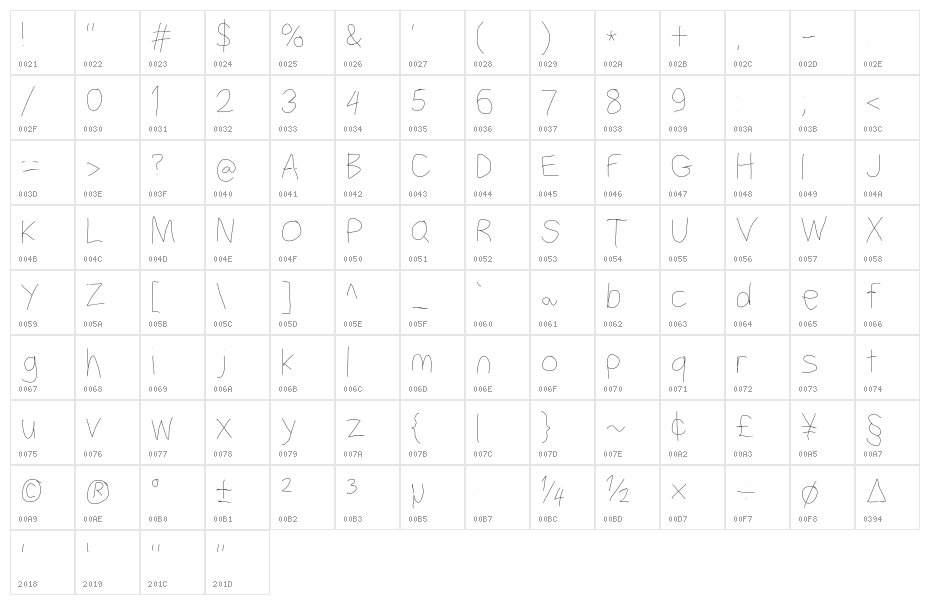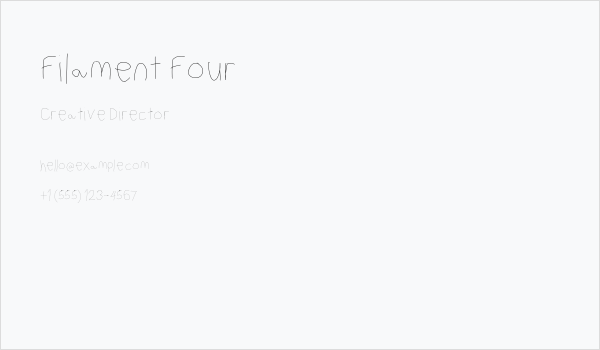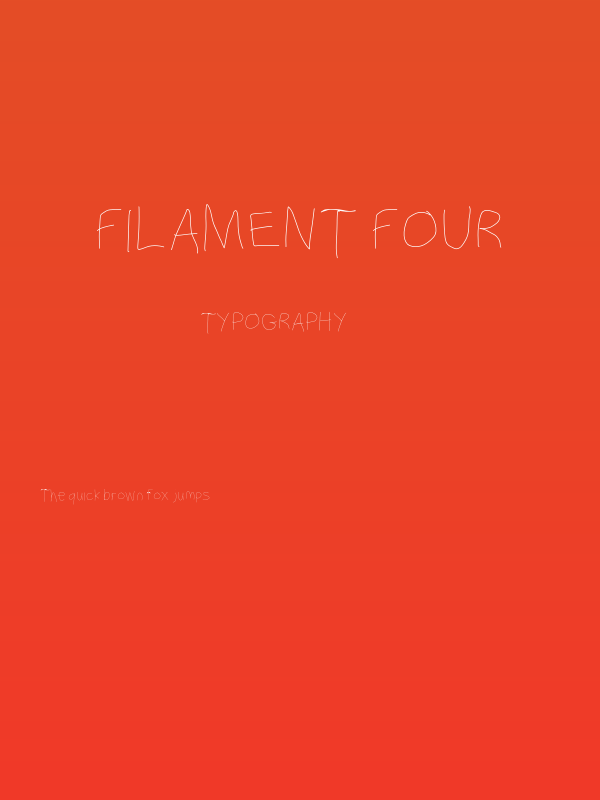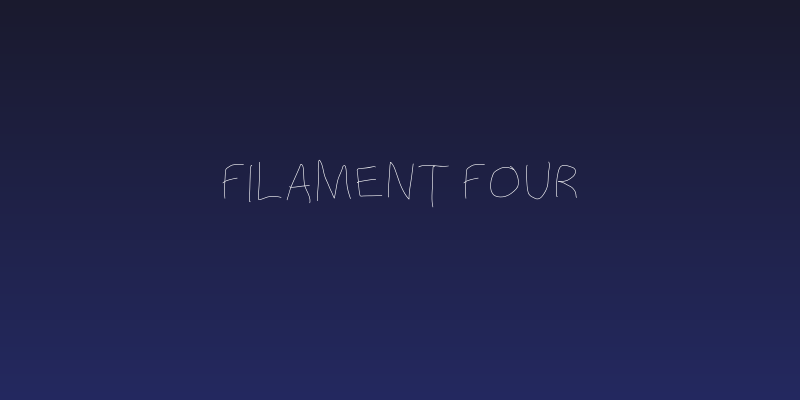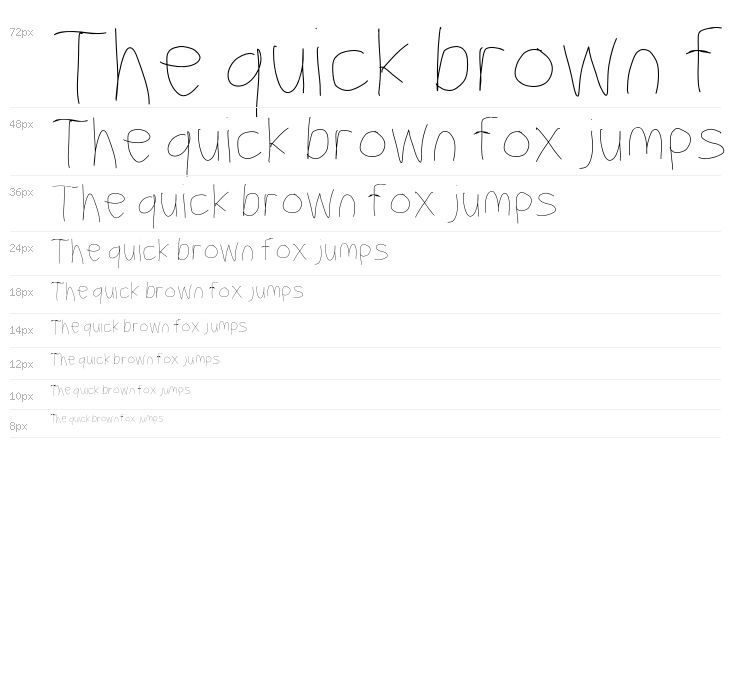
Filament Four Font
| Stile generale | Casual, Playful |
| Caso d'uso | Headlines, Informal Text, Creative Projects |
| Progetti proposti | Ideal for children's books, creative invitations, casual branding, and playful social media graphics. |